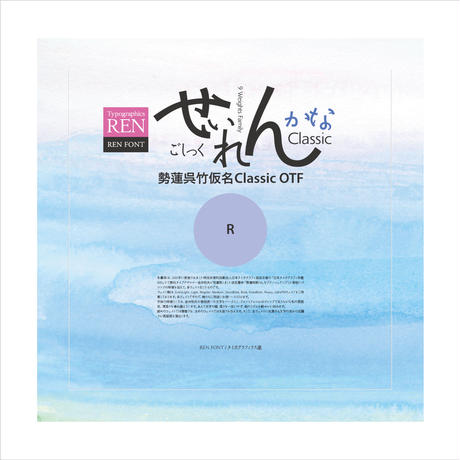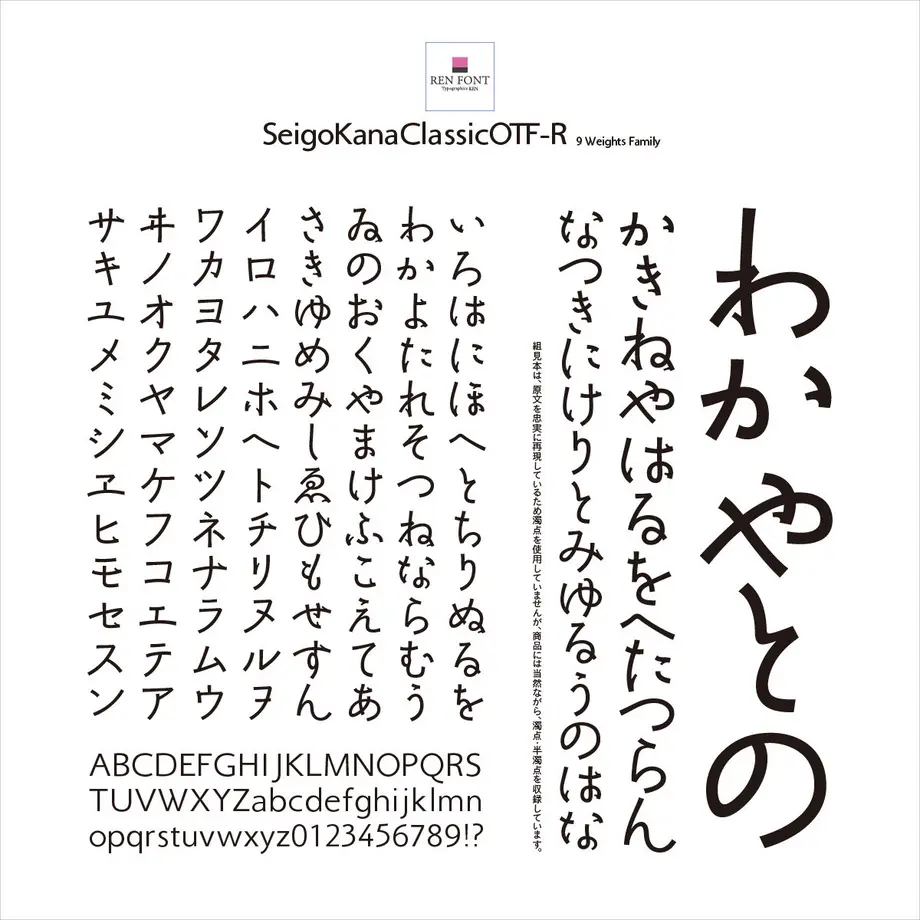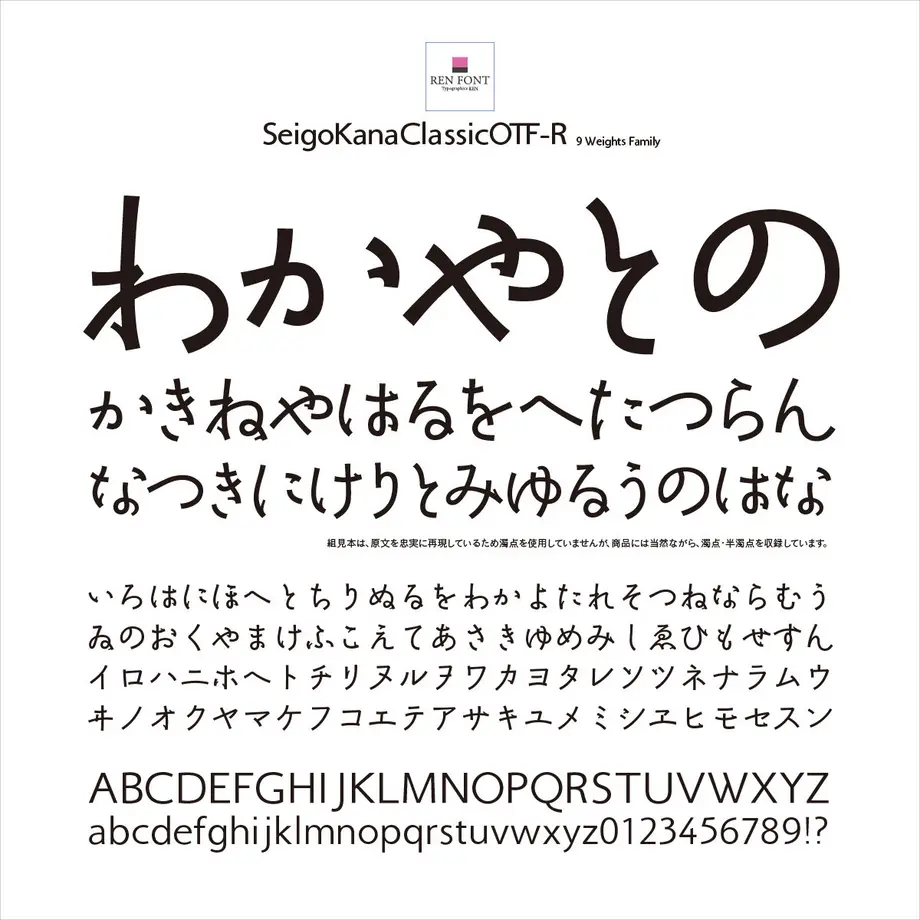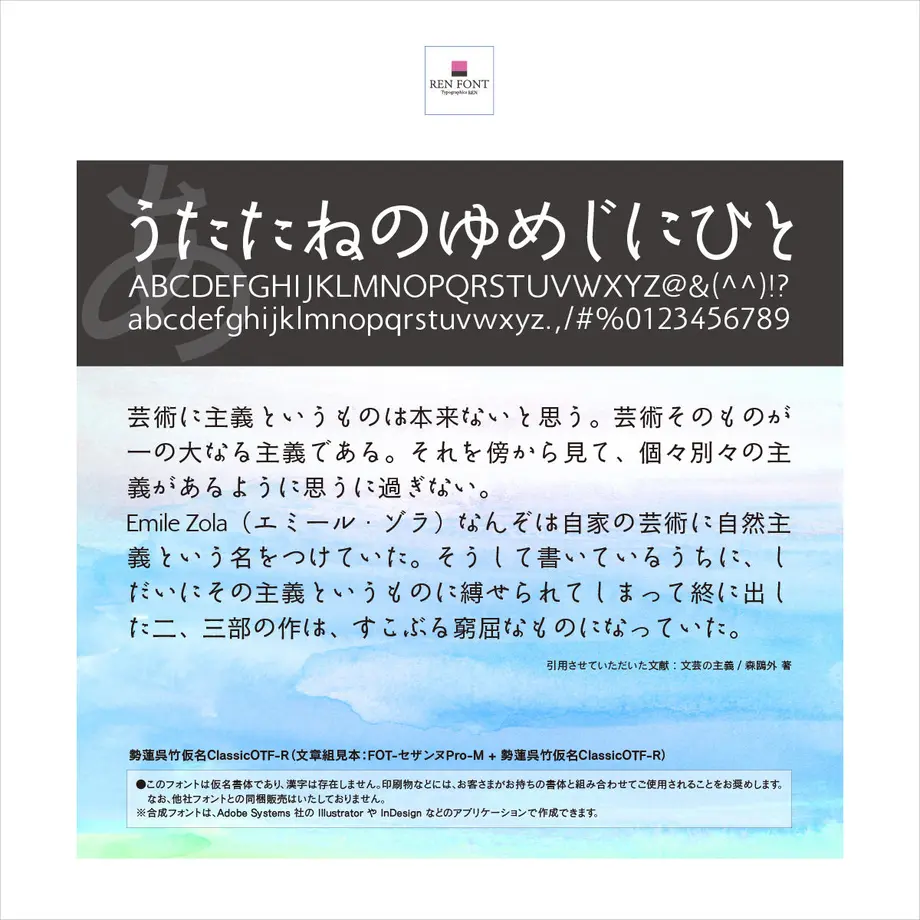
本書体は、2001年に実施されました特定非営利活動法人日本タイポグラフィ協会主催の「日本タイポグラフィ年鑑2001」にて弊社タイプデザイナー金井和夫が受賞致しました仮名書体「勢蓮明朝-M」をブラッシュアップした骨格にゴシックの特徴を加えて、多ウェイト化したものです。
ウェイト数はExtraLight、Light、Regular、Medium、DemiBold、Bold、ExtraBold、Heavy、Ultra の9ウェイトをご用意しております。多ウェイトですので、様々なご用途にお使いいただけます。
字体の特徴としては、金井和夫の普段使いの文字をベースとし、フォントフォルムはゴシックでありながら和の雰囲気、清潔さを兼ね備えています。あえて文字の幅・高さを一定にせず、組のリズムを軽やかに刻みます。
細めのウェイトでは華奢さを、太めのウェイトでは大胆さを与えます。そして、全ウェイトに共通する文字の流れの流麗さが高級感を演出します。